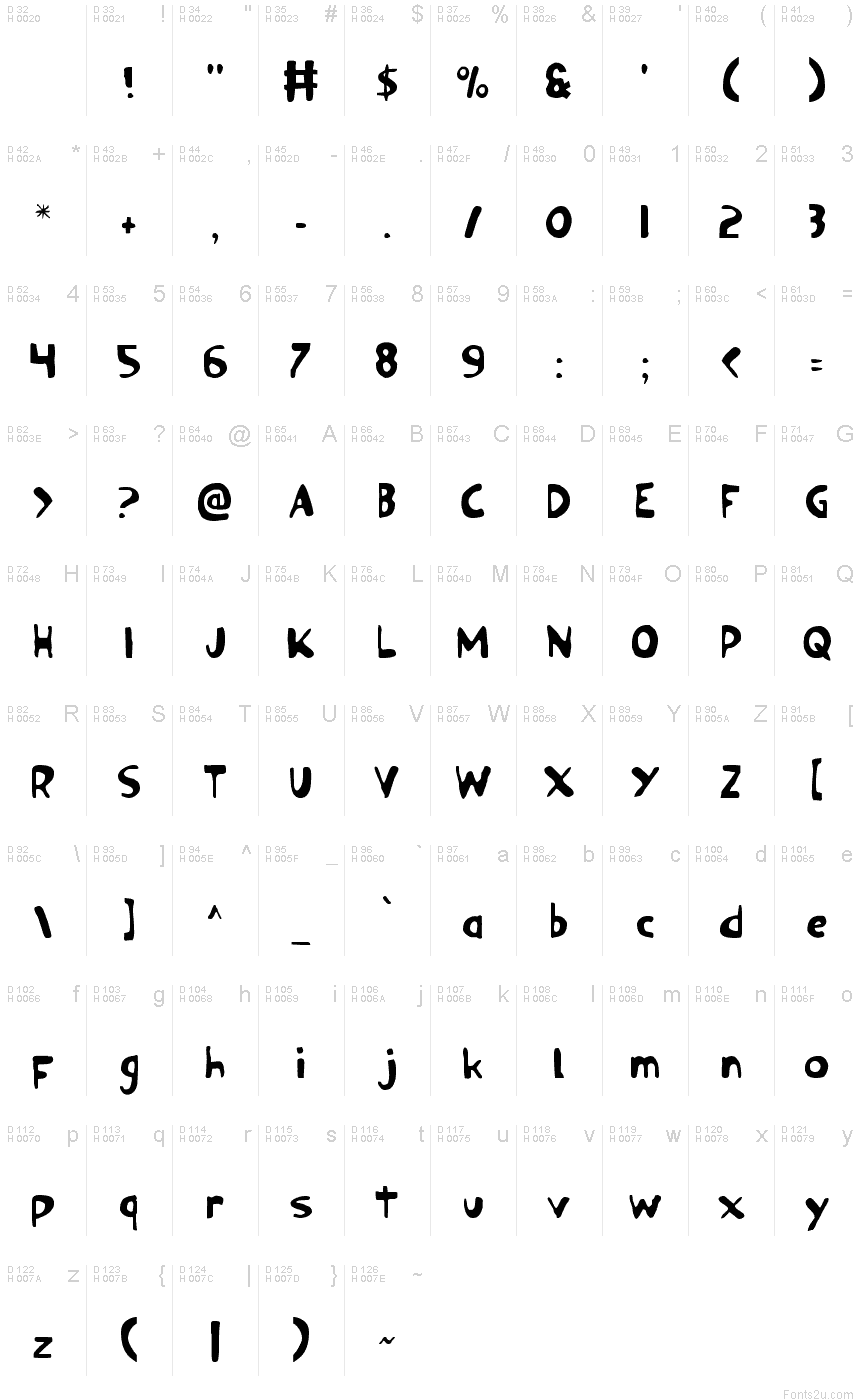
Ozymandias
Ozymandias od Iconian Fonts to bezpłatny komiksowy krój pisma o nieformalnym, ręcznie rysowanym charakterze. Litery mają nieregularną sylwetkę, dzięki czemu sprawiają wrażenie lekko ściśniętych, a jednocześnie przyjemnie napuchniętych. Ten nierówny rytm nadaje krojowi swobodny, „gumowy” wygląd, a zaokrąglone krzywizny i charakterystyczne łączenia odróżniają go od standardowych fontów rysunkowych.
Krótkie nagłówki, karty pracy dla dzieci, menu w grach, plakaty szkolne czy komiksowe dymki – to wszystko będzie wyglądać świetnie. Zaokrąglona bryła i dynamiczna linia bazowa sprawiają, że nawet krótki tekst nabiera wyrazistego, zabawnego charakteru. To idealny wybór do kreatywnego brandingu lub zaproszeń na imprezę, gdy zależy Ci na efekcie „hand-made” zamiast sterylnej doskonałości.